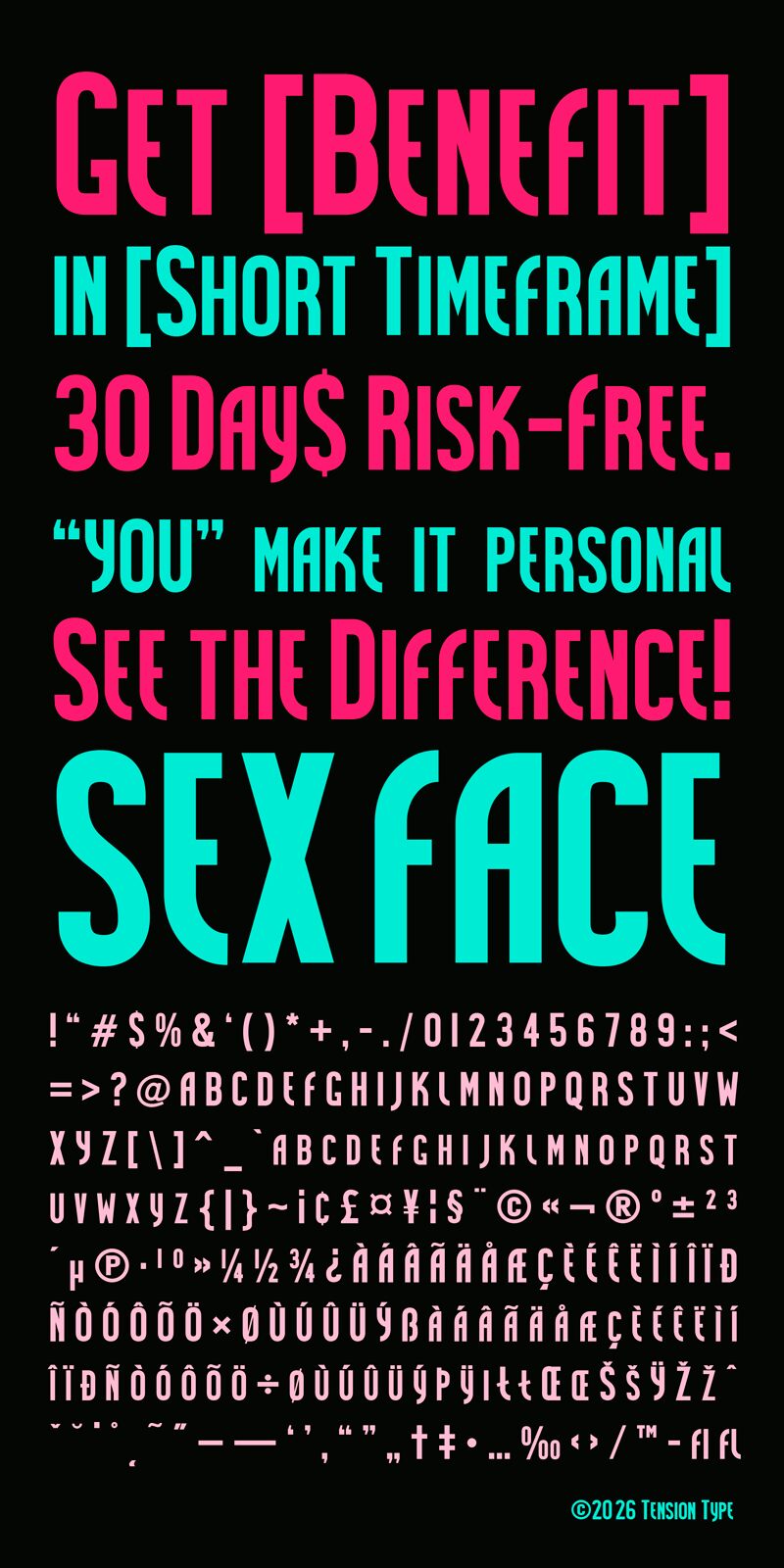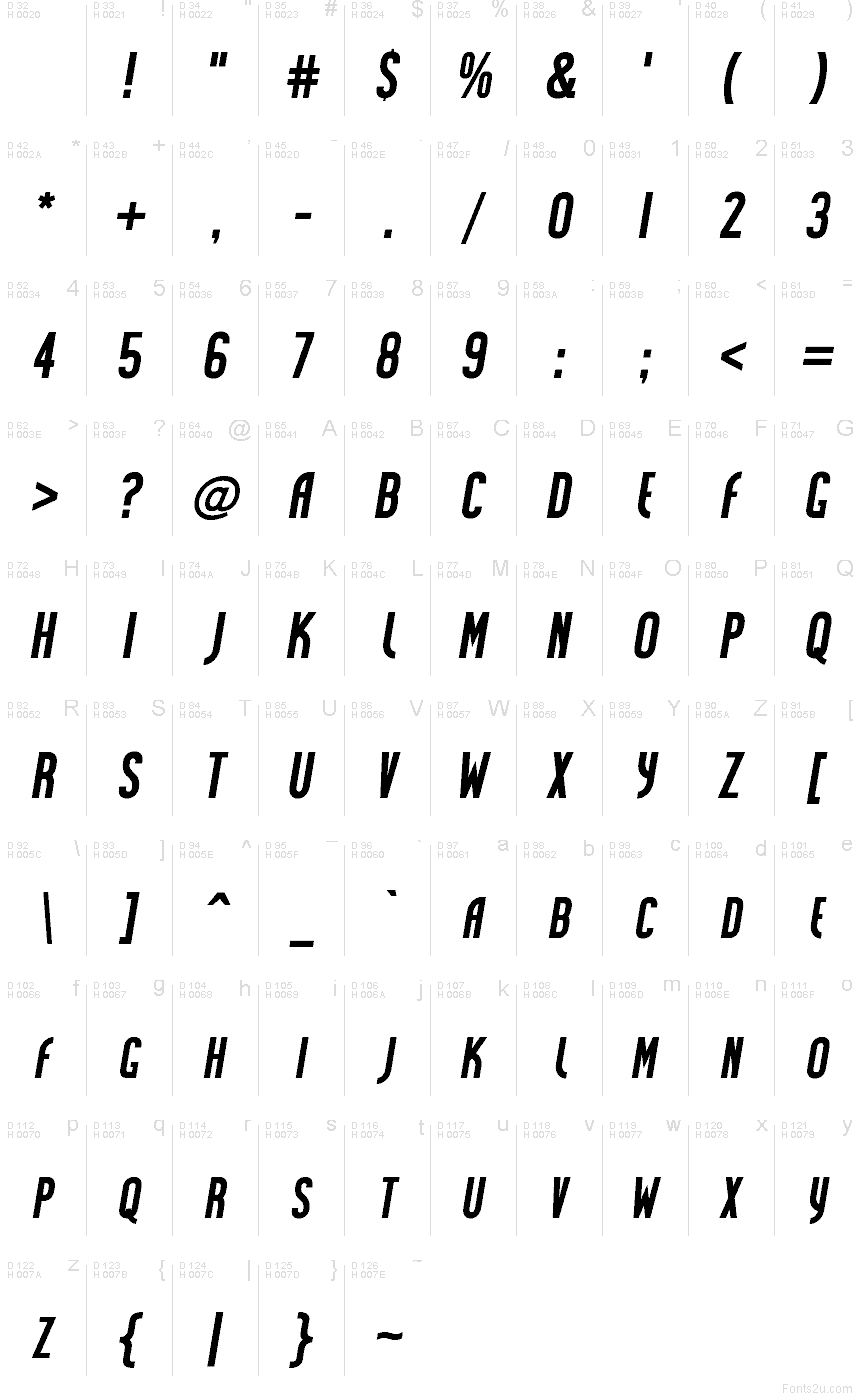
Sex Face Italic Small Caps
Sex Face Italic Small Caps es una tipografía sans serif gratuita con formas en versalitas inclinadas y curvas incisivas y afiladas. Las letras mantienen un ritmo estrecho y orientado hacia adelante, mientras que los elementos redondeados y las uniones angulares le otorgan un aspecto gráfico y decididamente comprimido.
Sex Face Italic Small Caps funciona muy bien en carteles, logotipos, portadas de música, packaging y titulares editoriales que necesiten un estilo compacto y a medida. Esta fuente gratuita es ideal para líneas cortas y acentos de marca, ya que su inclinación itálica y sus formas compactas se mantienen como una línea visual potente sin necesidad de decoraciones adicionales.
Mi segundo diseño de tipografía sans serif. Me gustan mucho las fuentes condensadas, así que eso es lo que hice. Ideal para titulares, carteles, logotipos o cualquier uso en tamaño grande. No es recomendable para texto principal.
Tension Type
Michael Tension
My second design of a sans serif font. I like condensed type a lot, so that’s what I did. A big learning curve!